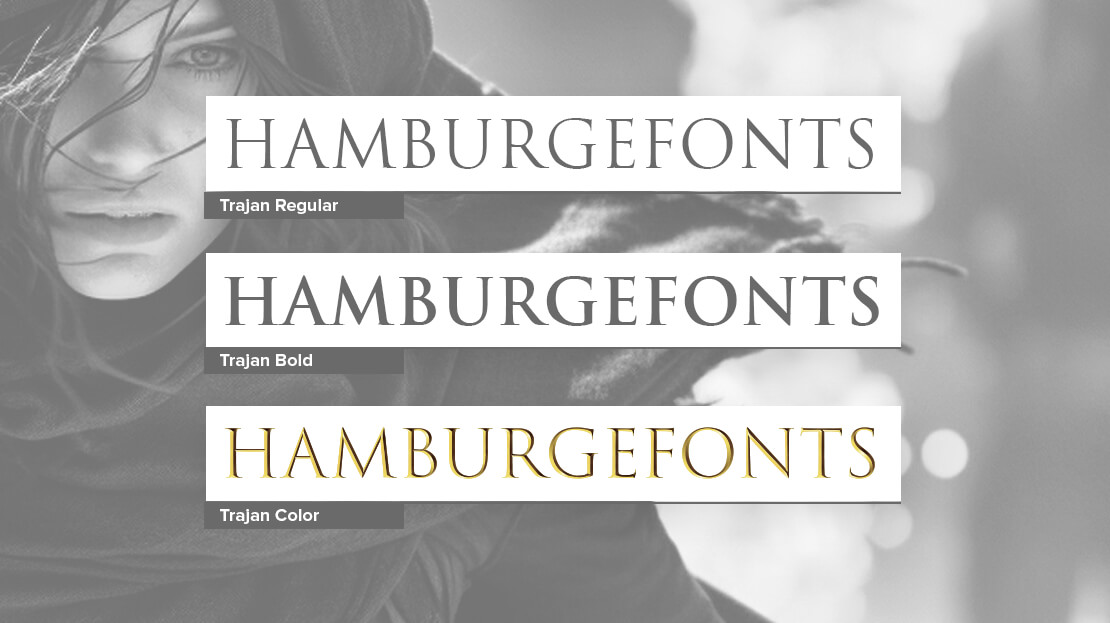
Schriftarten für Filme
Von epischen Dramen bis hin zu futuristischen Science-Fiction-Abenteuern – Typografie gibt Filmen eine Stimme, bevor überhaupt ein Wort gesprochen wird. Über die Wahl von Schriftarten, beliebte Film-Fonts, Klassiker und mehr.
Bedeutung der Typografie im Film
Typografie im Film erfüllt verschiedene Funktionen, die von der Vermittlung von Emotionen bis zur Etablierung der filmischen Welt reichen. In einem Horrorfilm kann eine kantige, bedrohliche Schriftart das Gefühl von Unbehagen verstärken, während in einer romantischen Komödie oft weichere und verspieltere Schriften verwendet werden, die Leichtigkeit und Unbeschwertheit ausstrahlen. Ein Science-Fiction-Film wiederum setzt häufig auf futuristische, geometrische Schriften, die den Zuschauer in eine technologische oder dystopische Welt versetzen sollen.
Die Wahl der richtigen Schriftart kann für erhöhte Aufmerksamkeit beim Publikum sorgen und die Botschaft des Films klarer vermitteln. Diese typografischen Entscheidungen können subtil sein, haben aber oft eine starke Wirkung. Beispielsweise ruft die Verwendung von Großbuchstaben und klaren Linien Stärke und Ernsthaftigkeit hervor, während handgeschriebene oder kurvige Schriftarten häufig eine intimere und persönlichere Atmosphäre erzeugen.
Ein weiterer Aspekt ist die Wiedererkennung. Manche Filme oder Filmreihen nutzen ikonische Schriftarten, die mit der Zeit zu ihrem Markenzeichen werden. Die Titelgestaltung von Filmen wie „Star Wars“ oder „Harry Potter“ ist stark mit ihrer jeweiligen Franchise verbunden und ruft sofort Bilder und Emotionen hervor, die das Publikum mit der Handlung, den Figuren und der Atmosphäre assoziiert. Auch auf Postern, in Trailern und bei Merchandise-Artikeln wird diese typografische Identität konsequent eingesetzt, was die Bindung und den Wiedererkennungswert weiter steigert.
Zusätzlich dient die Typografie als narrativer Einstieg in den Film. Die Schriftgestaltung eines Eröffnungsbildes oder Filmtitels kann Hinweise auf die Zeit, den Ort und das soziale Umfeld des Films geben. Historische Filme greifen beispielsweise häufig auf klassische, serifenbetonte Schriften zurück, die Assoziationen zu vergangenen Epochen herstellen. Moderne Thriller hingegen bevorzugen oft minimalistische, serifenlose Schriftarten, die zur urbanen, nüchternen Atmosphäre solcher Filme passen.
Letztlich zeigt sich, dass Typografie im Film weit mehr ist als nur eine ästhetische Entscheidung. Sie ist ein erzählerisches Werkzeug, das dazu beiträgt, die Welt des Films zu formen, Emotionen zu wecken und das Publikum zu leiten – ein stummer, aber wirkungsvoller Prolog, der die Tür zur filmischen Erzählung öffnet und einen ersten Eindruck hinterlässt, noch bevor die Geschichte beginnt.
Designprozess von Filmpostern
Akiko Stehrenberger, eine erfahrene Filmposter-Designerin, betont in einem Beitrag im Adobe-Blog die Bedeutung des Brainstormings von Ideen, um ein tiefes Verständnis für den Film zu erlangen. Egal ob Indie-Streifen, historisches Drama oder mitreißendes Action-Spektakel – Genre und die Stimmung des Films spielen eine entscheidende Rolle bei der Auswahl und Kombination von Bildern und Schriftarten.
Sobald der visuelle Stil des Films definiert ist, steht die Wahl der passenden Design-Techniken für das Filmplakat an. Dabei gilt es auch zu hinterfragen, wie man dem Publikum mit nur einem Bild und wenigen Textzeilen vermitteln kann, welche Erlebnisse der Film bereithält.
Schriftwahl für Filme
Auf den meisten Filmplakaten wird Text genutzt, um den Filmtitel, einen Leitspruch und die Filmcredits zu präsentieren. Doch selbst kurze Textelemente sollten ins Auge springen und gut lesbar sein.
Akiko Stehrenberger unterstreicht, dass das Genre und die Atmosphäre des Films beeinflussen, wie und in welchem Stil Bilder und Schriftarten eingesetzt werden. Dieser Ansicht schließt sich auch der Plakatdesigner Gabz Grzegorz Domaradzki an. In einem Artikel wird hervorgehoben, dass er die Typografie meistens zum Schluss berücksichtigt. Für ihn stellt es sowohl ein Vergnügen als auch eine Aufgabe dar, die ideal passende Schriftart auszuwählen.
Beliebte Schriftarten für Filmposter und Filme
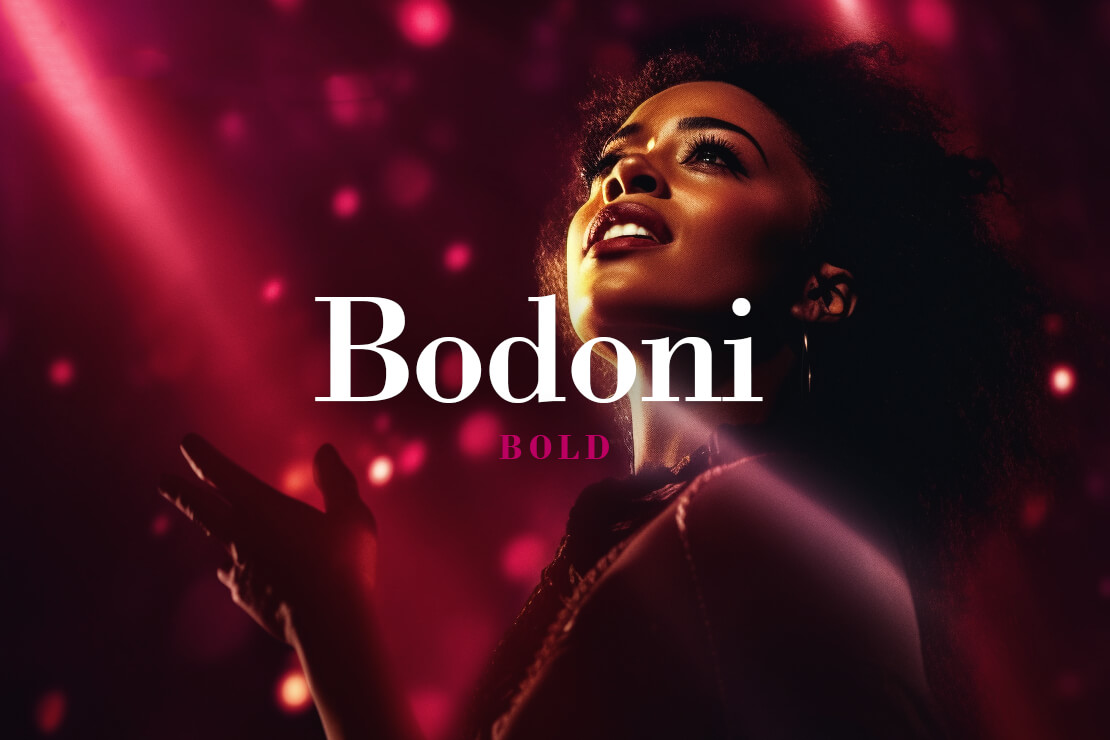
Bodoni
Bodoni dient als zentrale Schrift für zahlreiche Filmplakate, darunter „Mamma Mia“. Weitere Filme, die auf diese Schriftart setzen, sind „20 Feet From Stardom“, „Prisoners“ und „Water for Elephants“.
Garamond
Der Film „The World’s End“ hat diese Schriftart effektiv in seinem Filmplakat eingesetzt. Auch für Plakate von „Nottinghill“, „Mr. and Mrs. Smith“ und „Marley and Me“ kommt Garamond in unterschiedlichen Versionen zum Einsatz.
Futura
Der Film „The Hangover“ setzt beispielsweise auf Futura, um seinem Haupttitel eine klare Optik zu verleihen. Die Schriftart findet ebenso Anwendung auf den Filmplakaten von „Life of Pi“ oder „Gravity“.
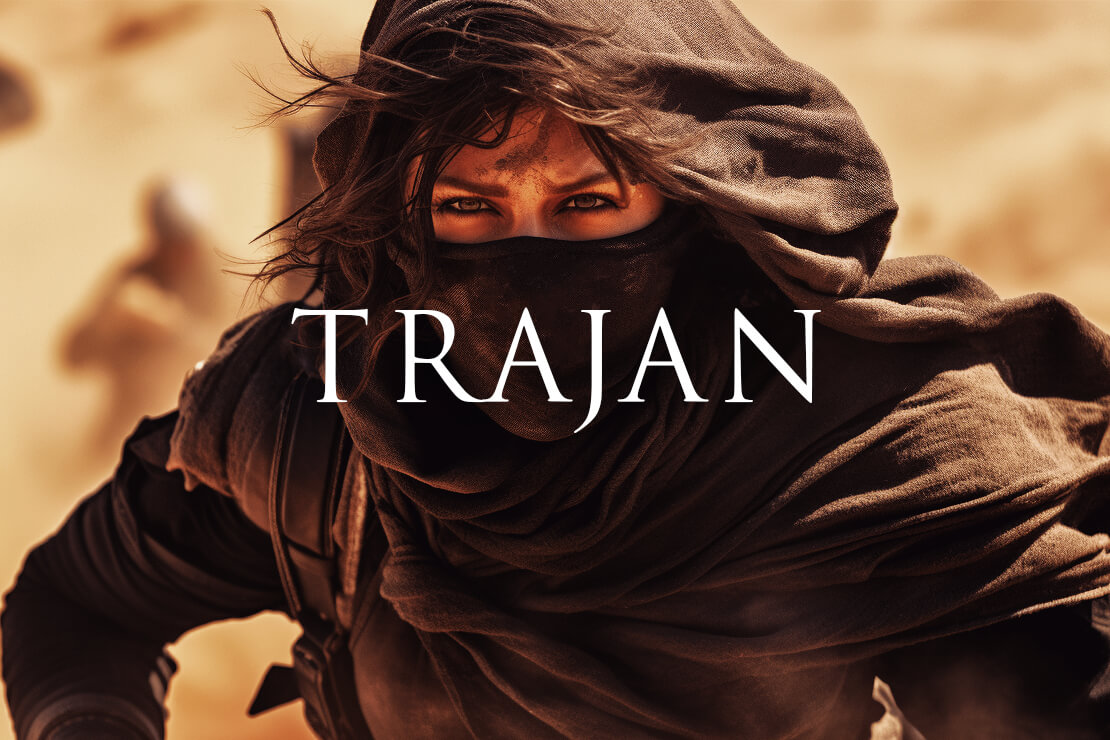
Trajan
Diese Schriftart findet oft in Horror- oder Thriller-Filmen Anwendung. Beispielsweise wird Trajan im offiziellen Filmposter zu „Black Swan“ genutzt und erzeugt durch die spitzen Kanten und Großbuchstaben eine unheimliche Atmosphäre. Zu weiteren Filmen, bei denen Trajan Verwendung findet, gehören „Die Mumie“, „Master and Commander“, „The Final Destination“, „The Cabin In The Woods“ und „Memoirs of a Geisha“ oder auch Serien wie „Game of Thrones“.
Fazit
Die Typografie ist ein wesentlicher Bestandteil in der Gestaltung von Plakaten, im Motion Design und in Kulissen von Filmen. Außerdem ist es wichtig, die Schriftarten sorgfältig auszuwählen und anzupassen, um sich vom Überangebot der Filme abzuheben.